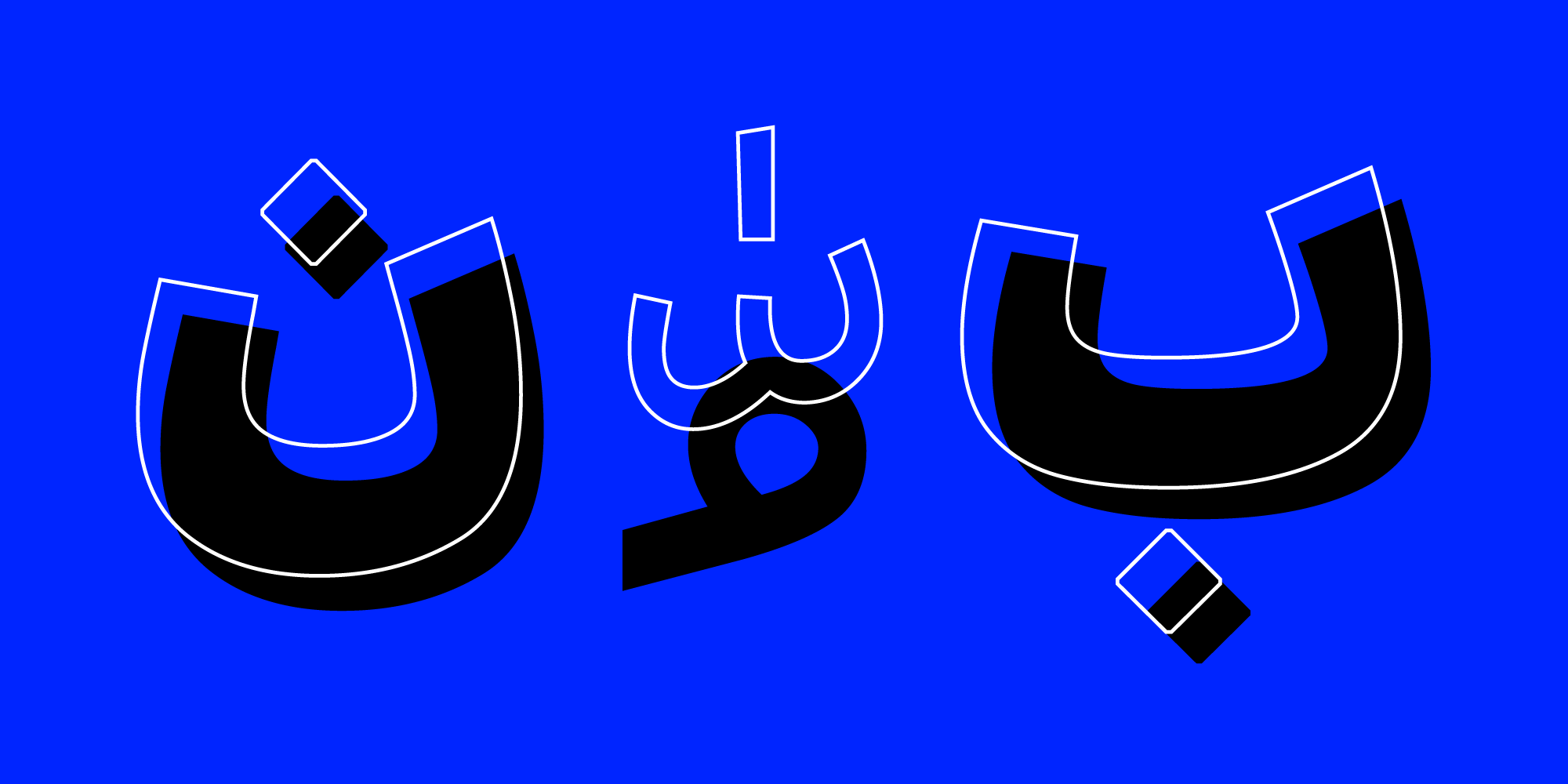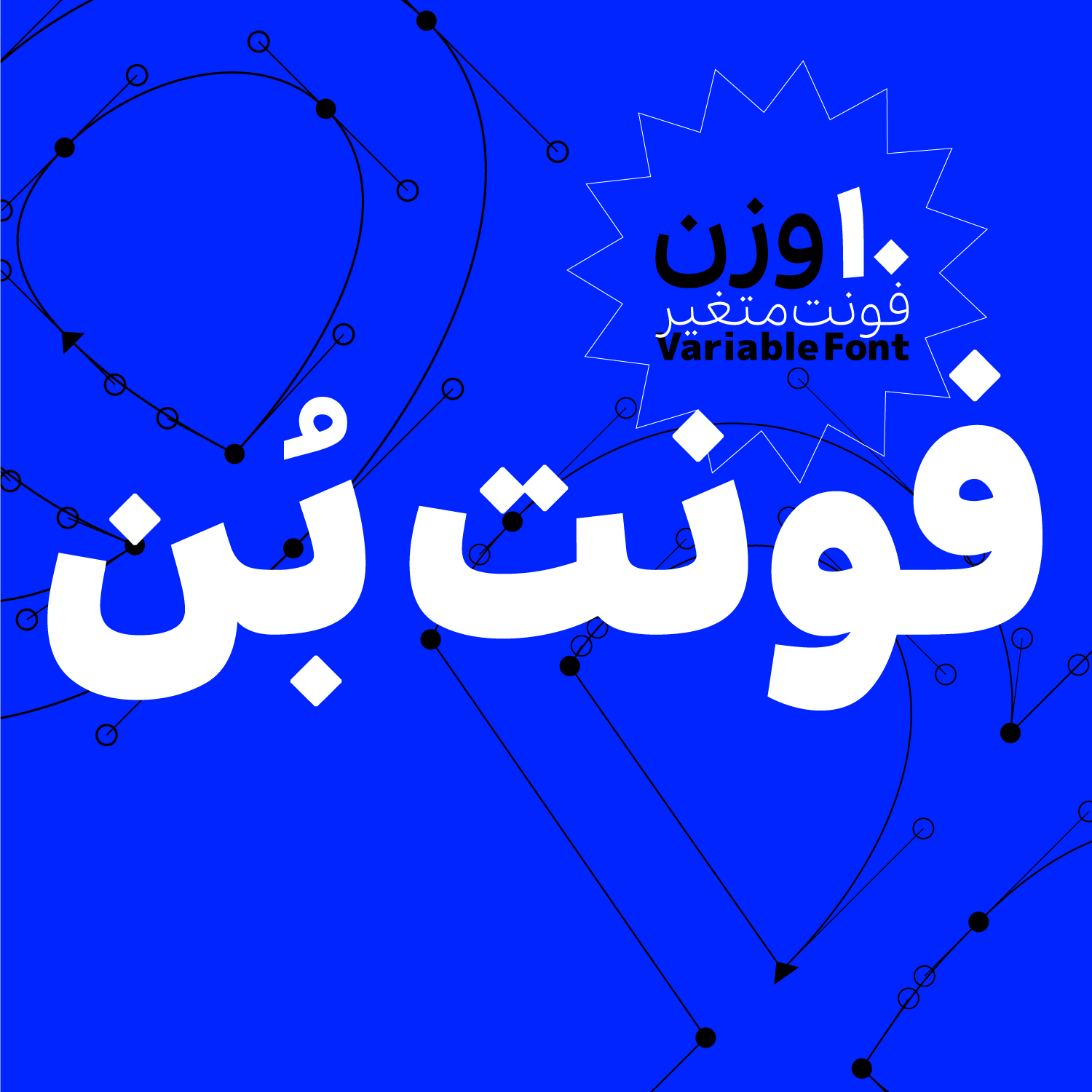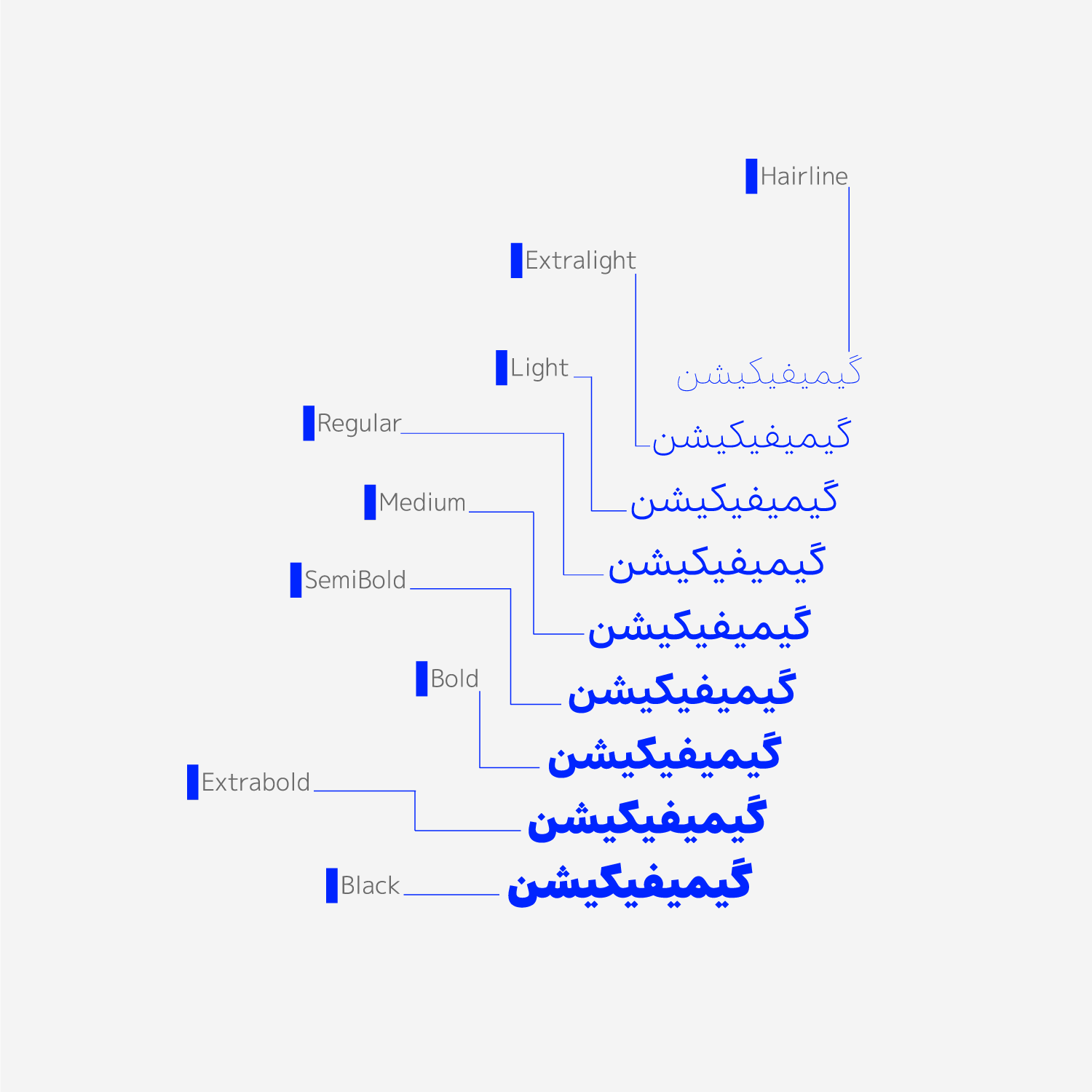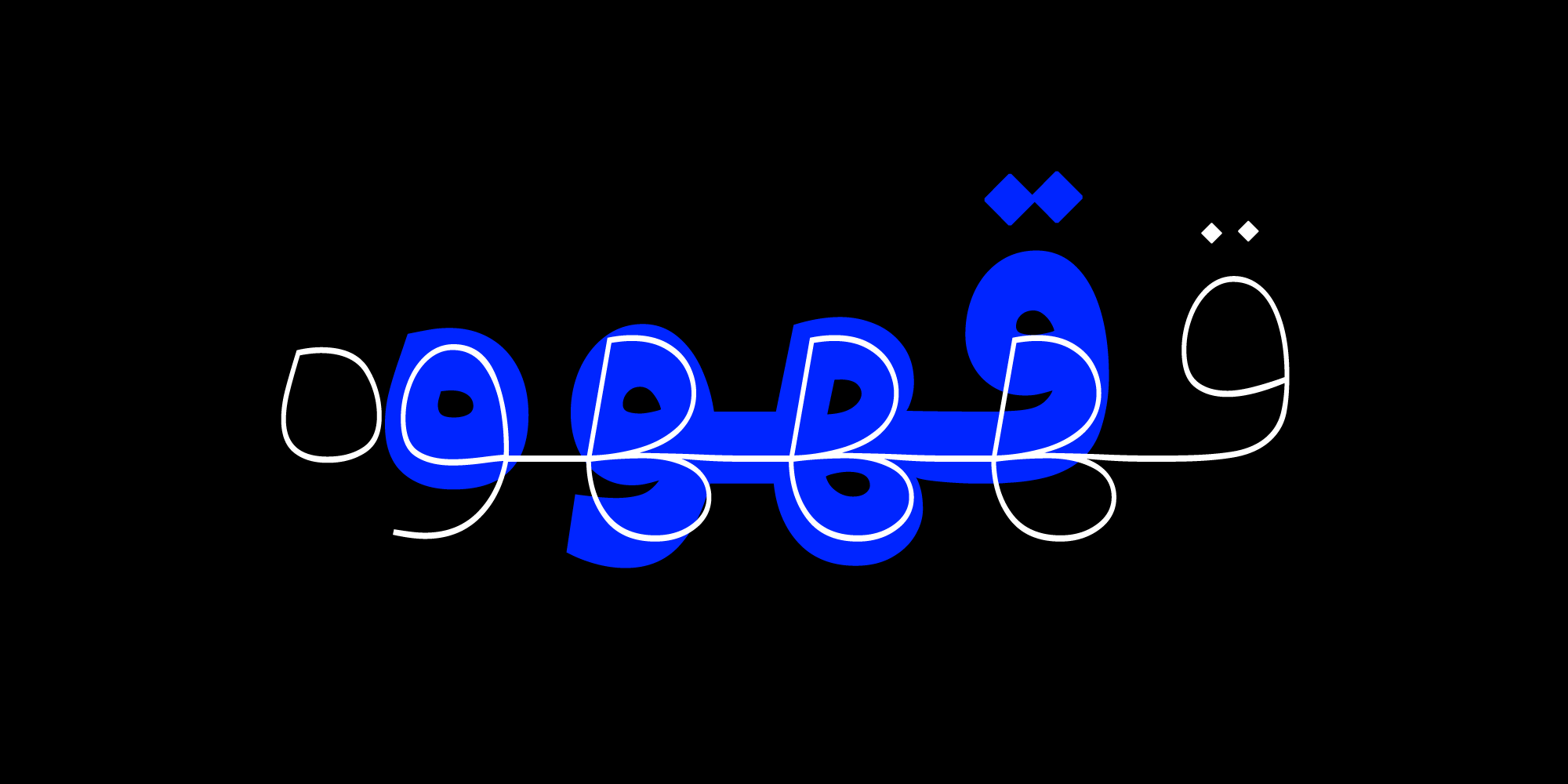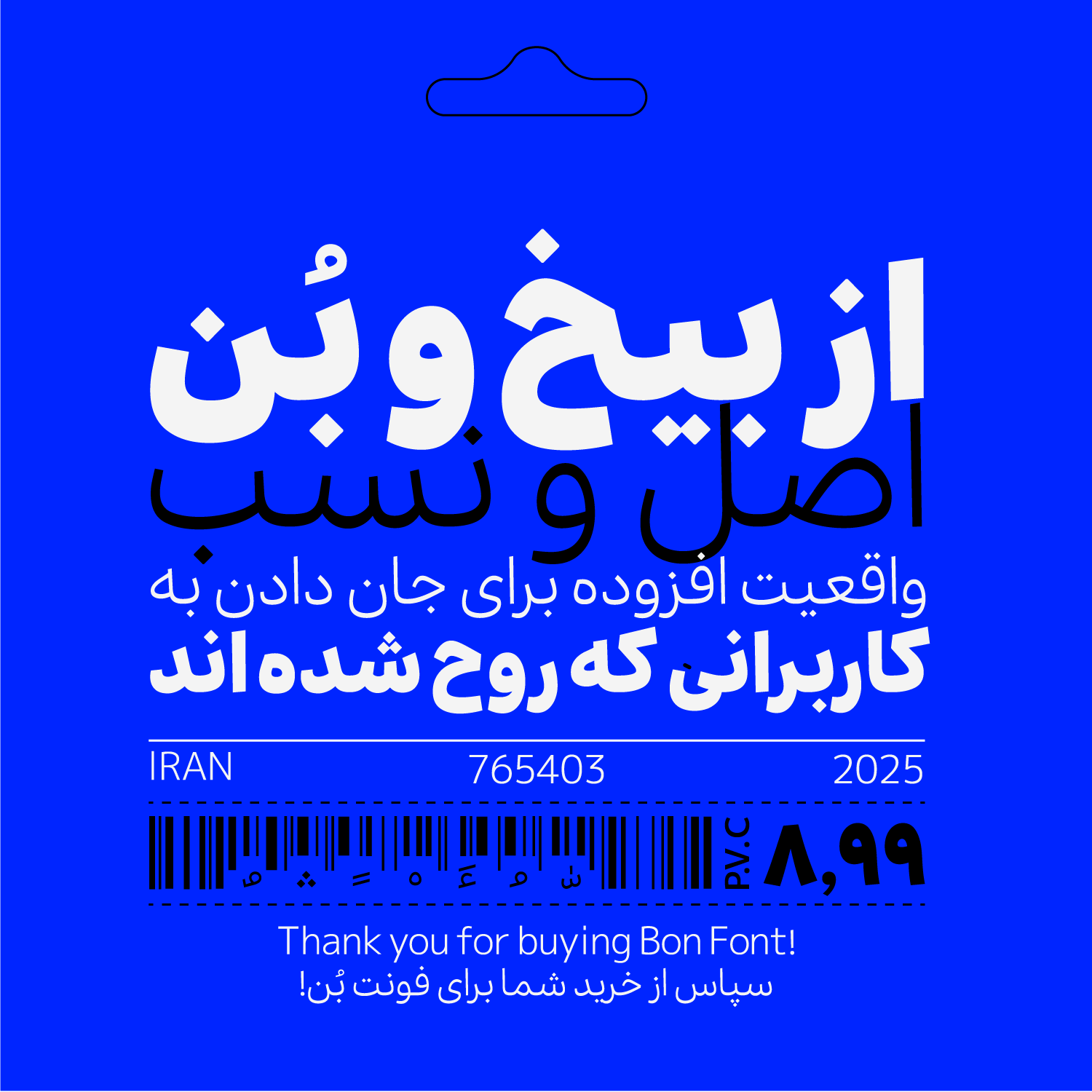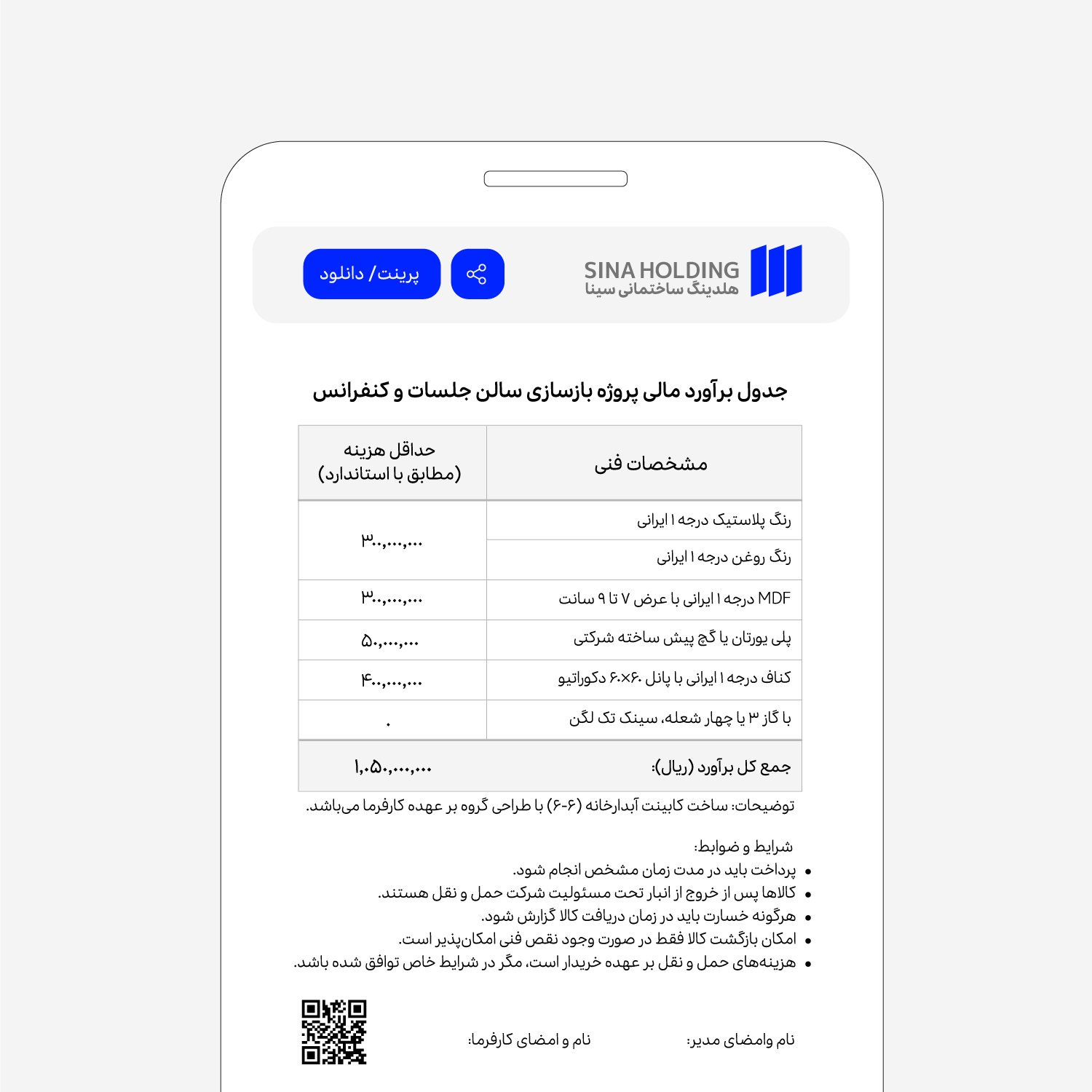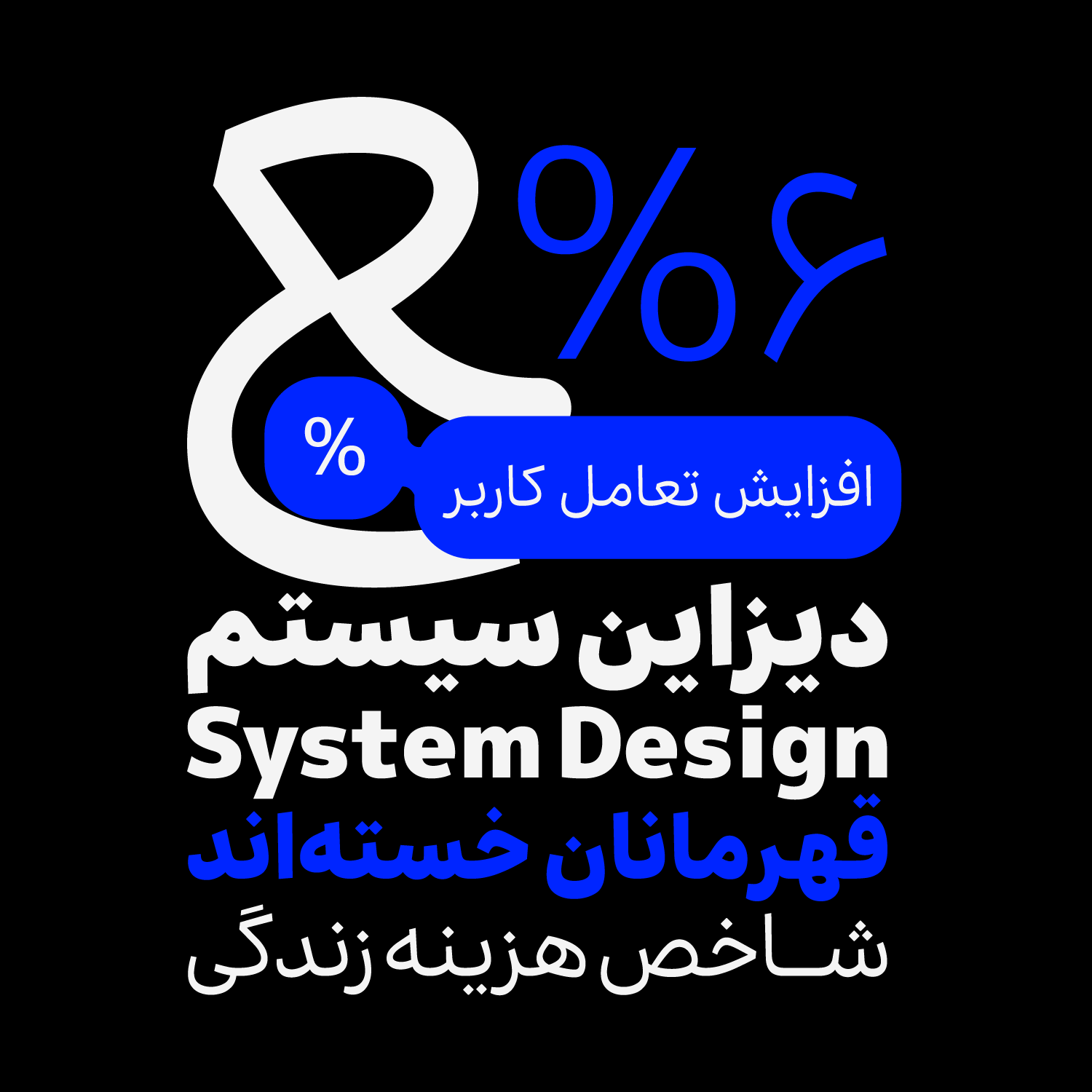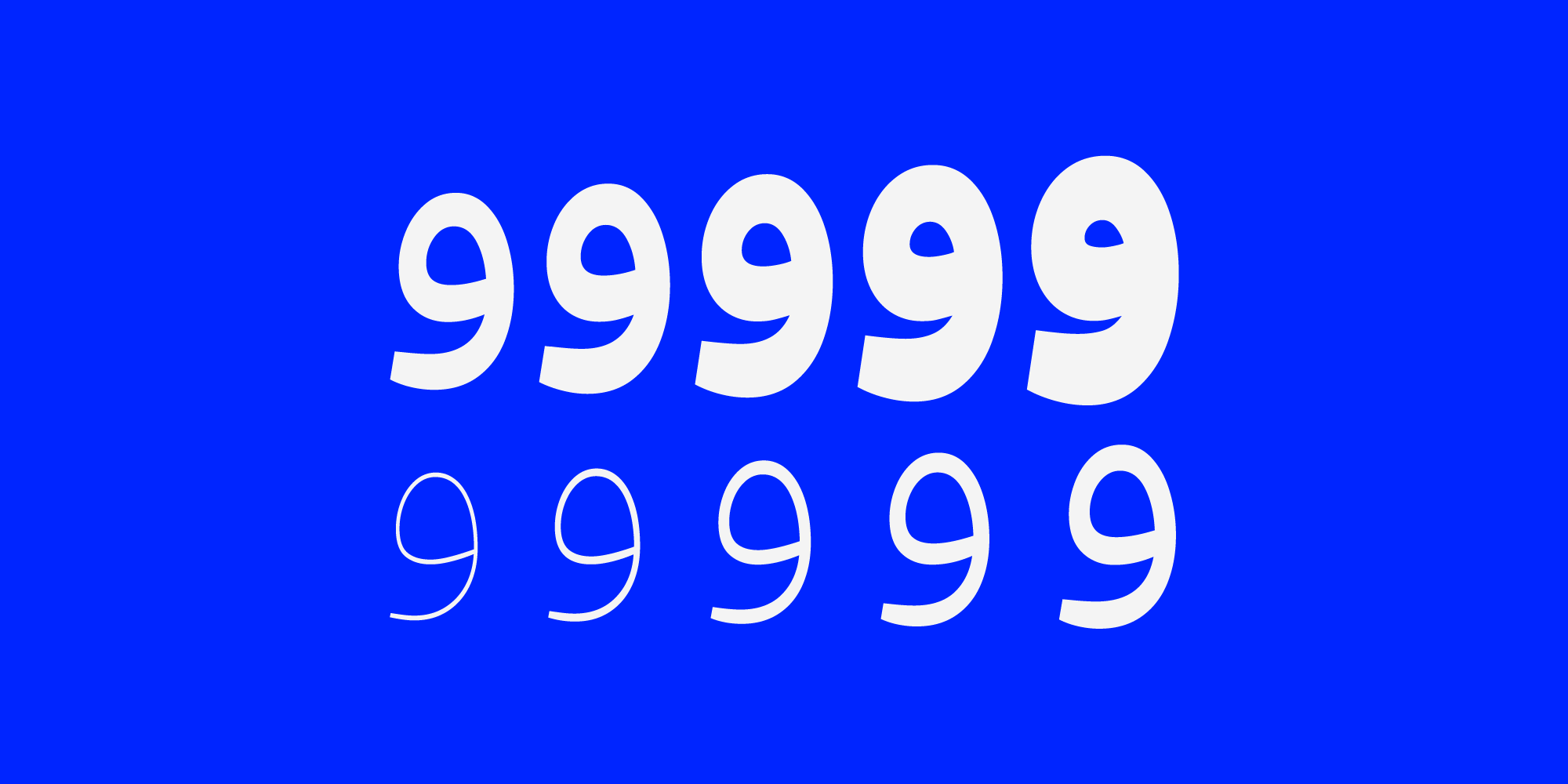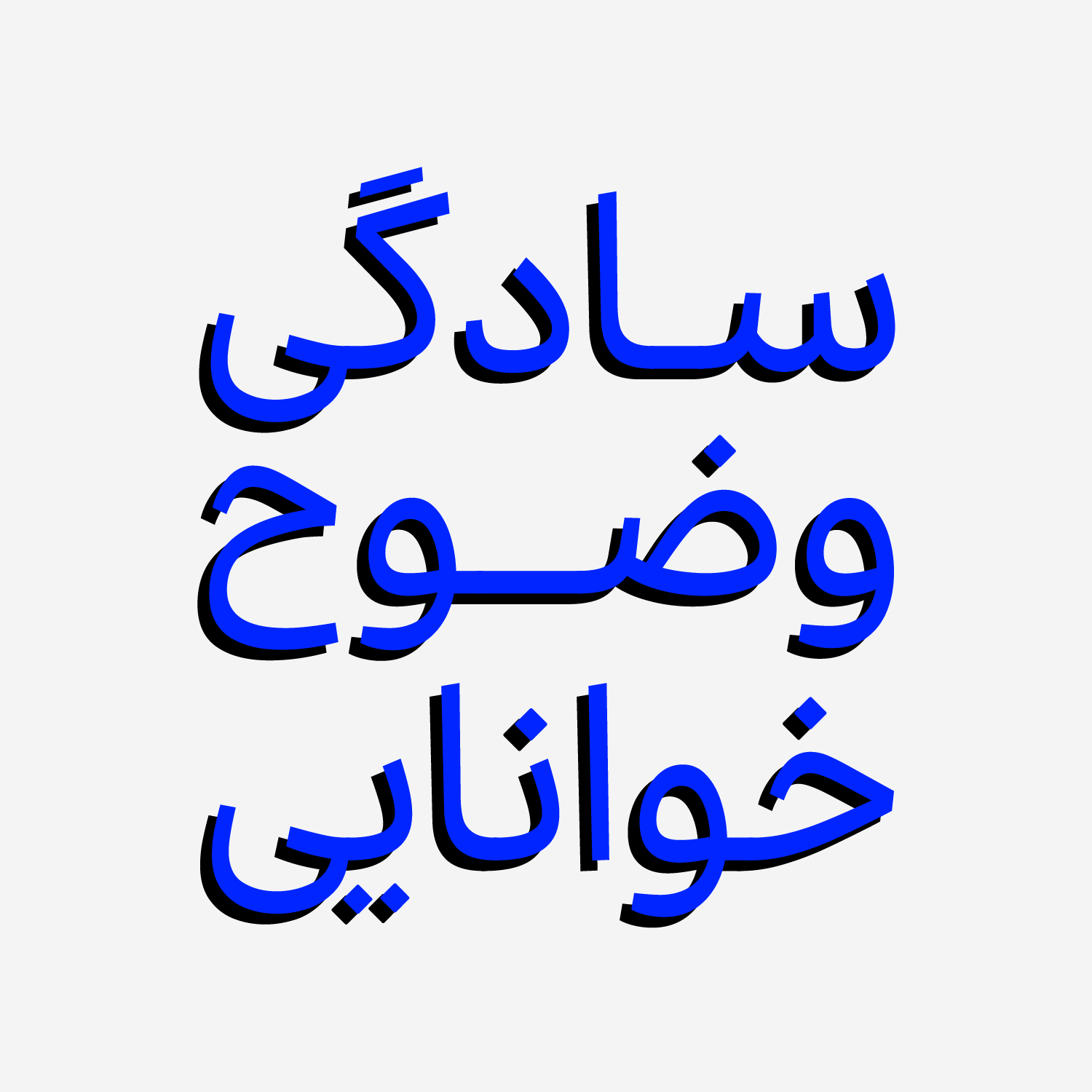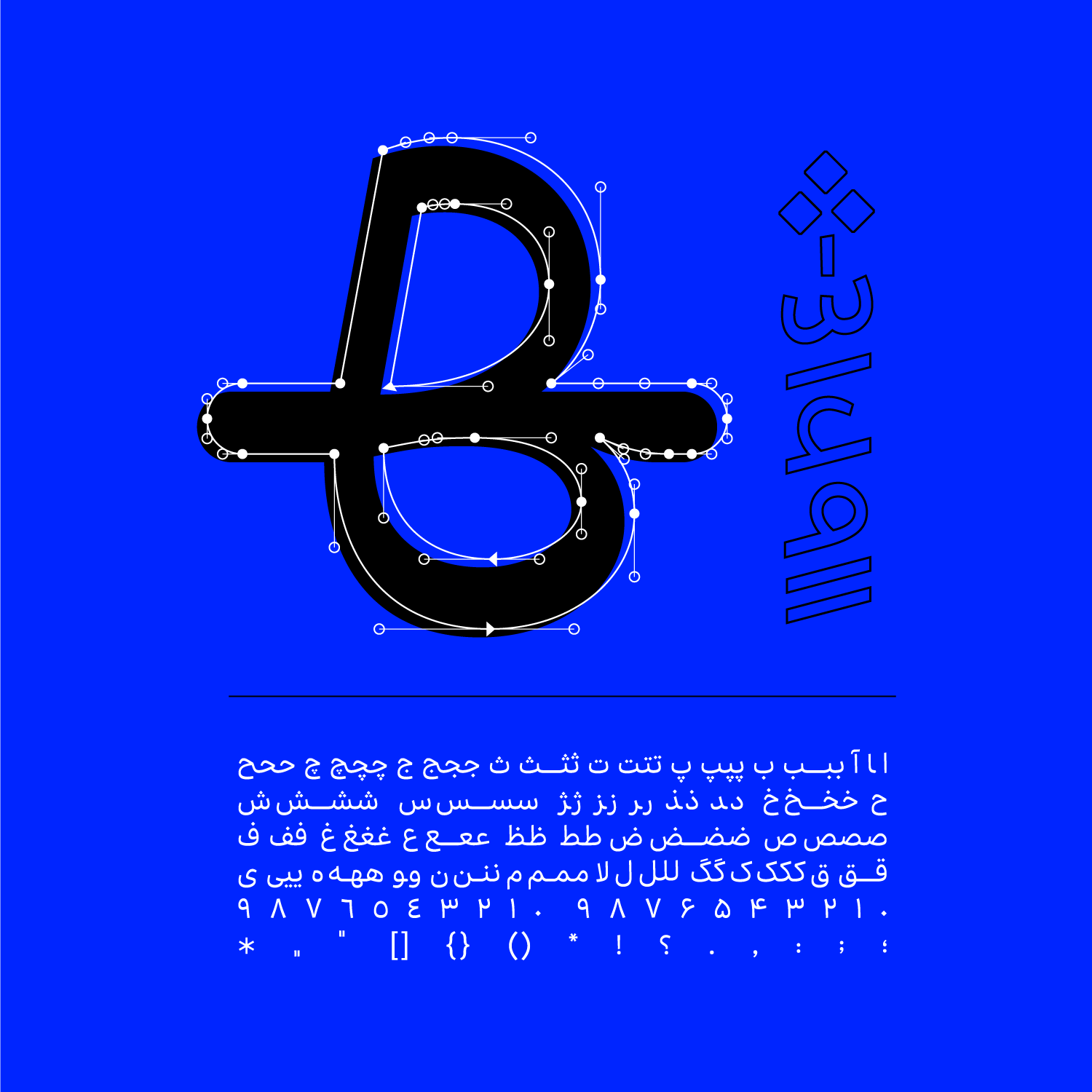
طراحی بُن با الهام از نسل تایپفیسهای کاربردی و روزمره که هویت بصری ما را شکل دادهاند، طراحی شده، اما نقش خود را در دنیای مدرن بهینهسازی کرده است. این فونت ضمن پایبندی به ساختارهای سنتی حروف، بر خوانایی، تعادل و روانی فرمها تأکید دارد.
تنوع وزنها در فونت بُن
بُن یک خانوادهی تایپفیس با ۱۰ وزن، از Hairline تا Black است که به طراحان امکان طیف گستردهای از وزنهای نوشتاری را میدهد. از نوشتههای ظریف و سبک تا نوشتههای قدرتمند و تأثیرگذار.
نام این فونت از واژهی فارسی "بُن" گرفته شده که به معنای ریشه، پایه و اساس است—تعریفی که کاملاً با ماهیت آن همخوانی دارد. بُن به عنوان یک ابزار پایه در سیستمهای تایپوگرافی طراحی شده است و خوانایی، تطبیقپذیری و عملکرد بیدردسر را بر تزئینات بصری ترجیح میدهد. این فونت بدون جلب توجه غیرضروری، بهراحتی در انواع فضاهای طراحی ادغام میشود.
بُن تلاش نمیکند تا خودنمایی کند؛ بلکه محتوا را در اولویت قرار میدهد. این فونت برای همراهی، نه سلطهگری طراحی شده است و تجربهای روان و بدون اختلال در خواندن را فراهم میکند. حضور آن در جعبه ابزار یک طراح نهتنها مفید، بلکه ضروری است و امکان استفاده در فضاهای متنوع چاپی و دیجیتال را فراهم میکند